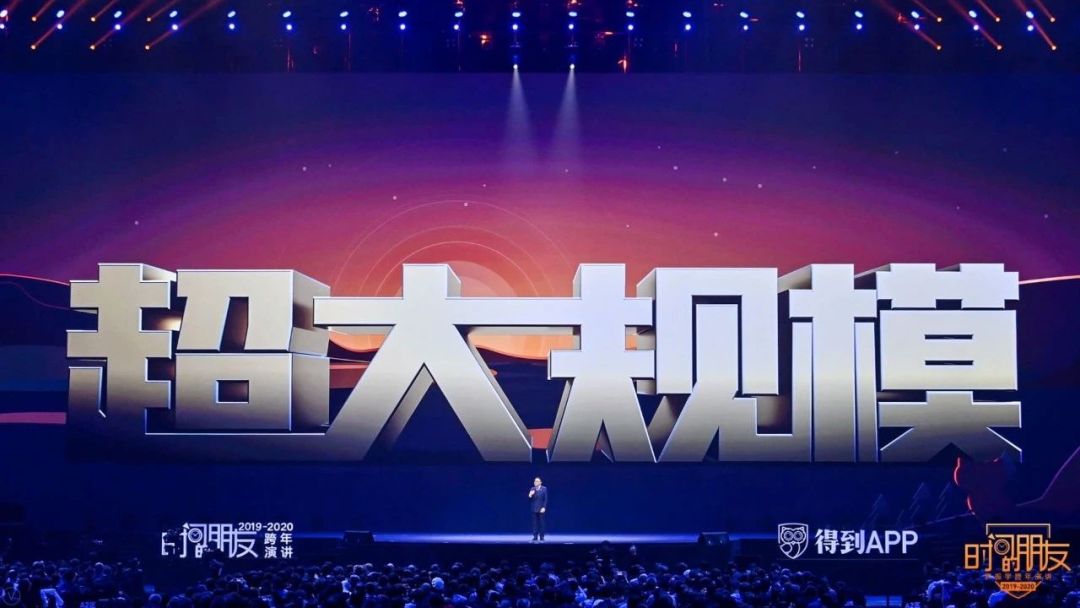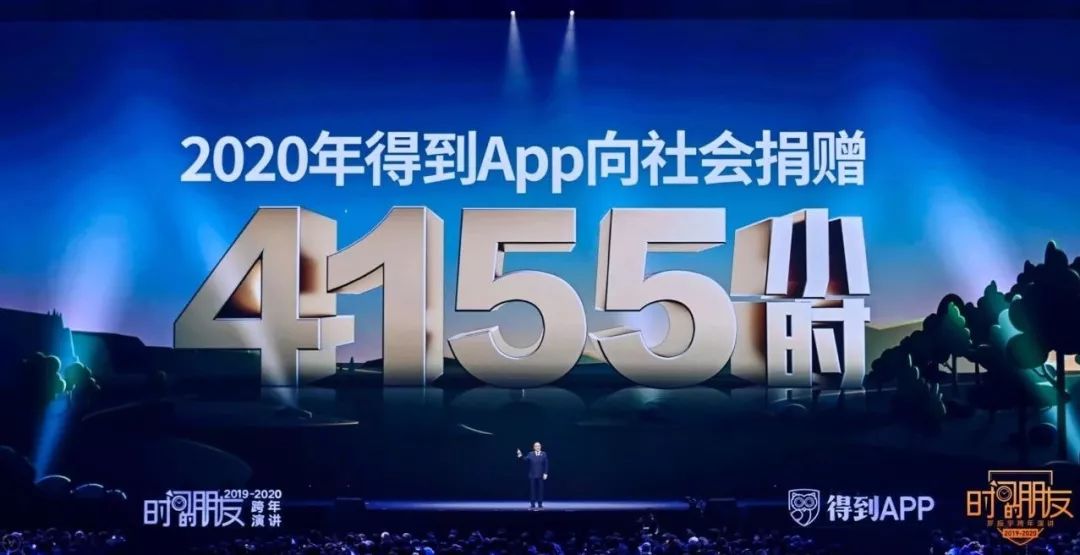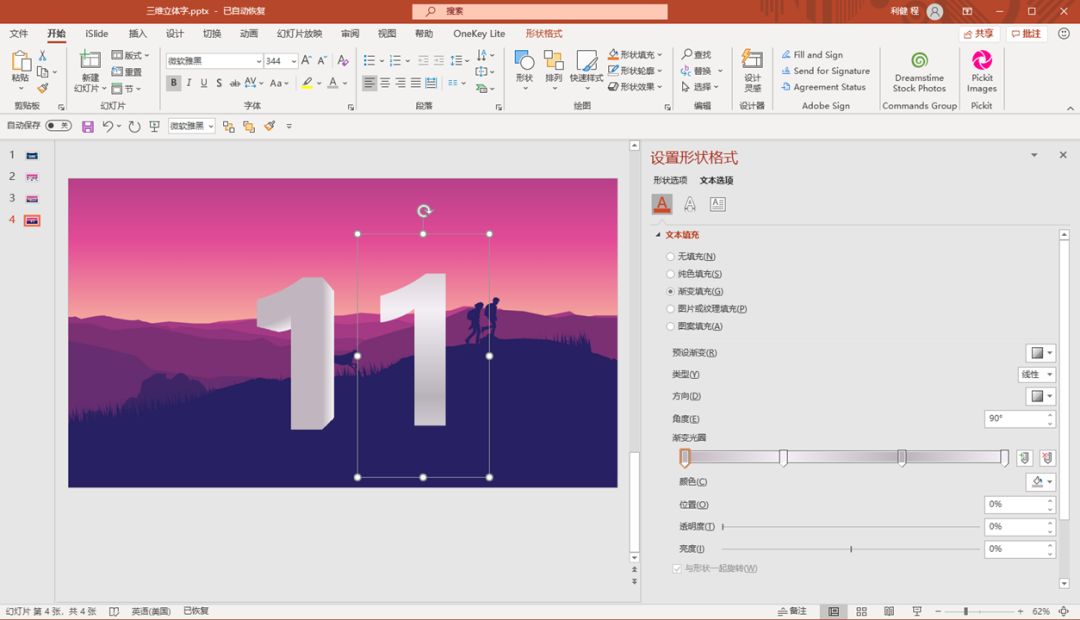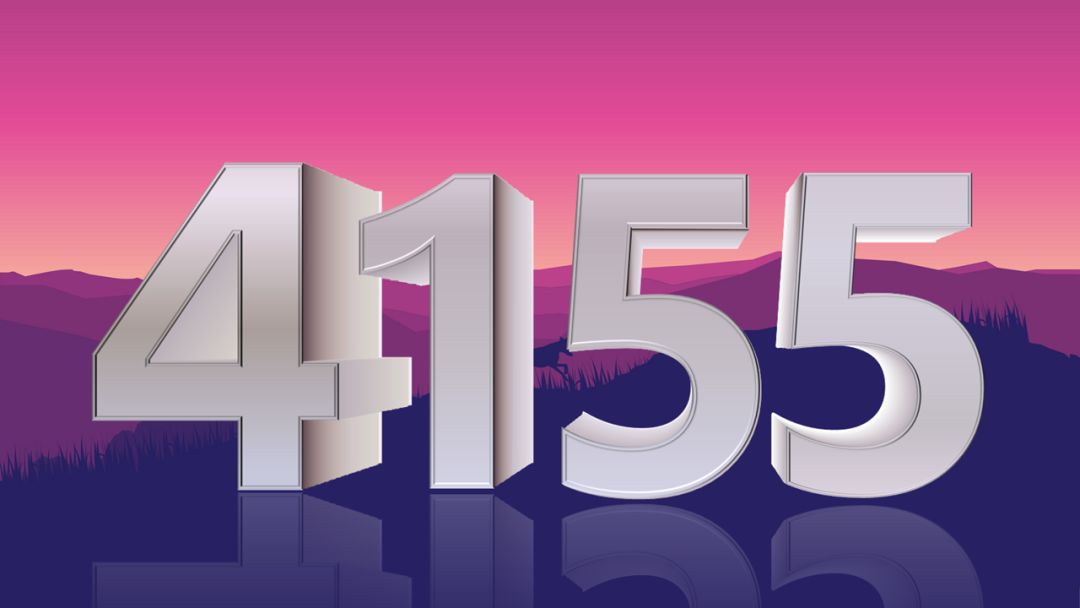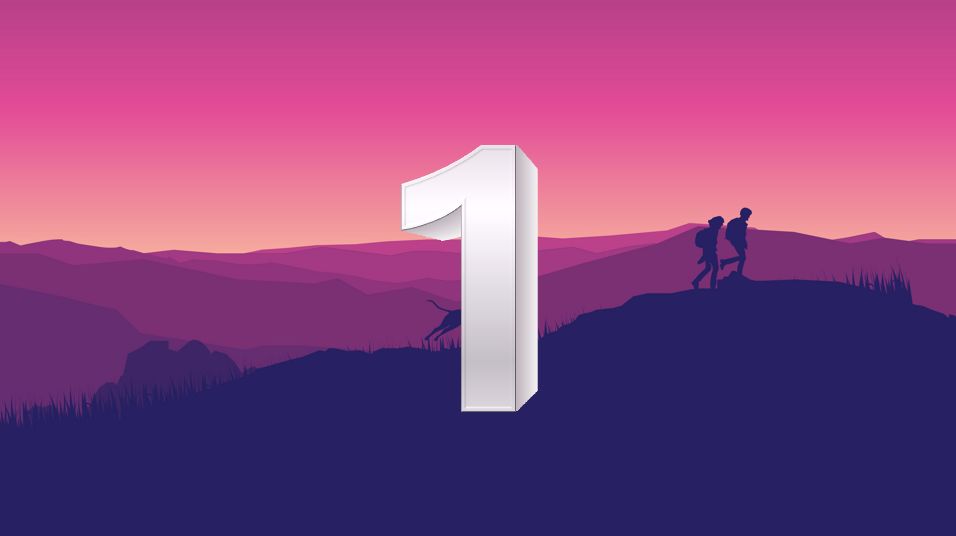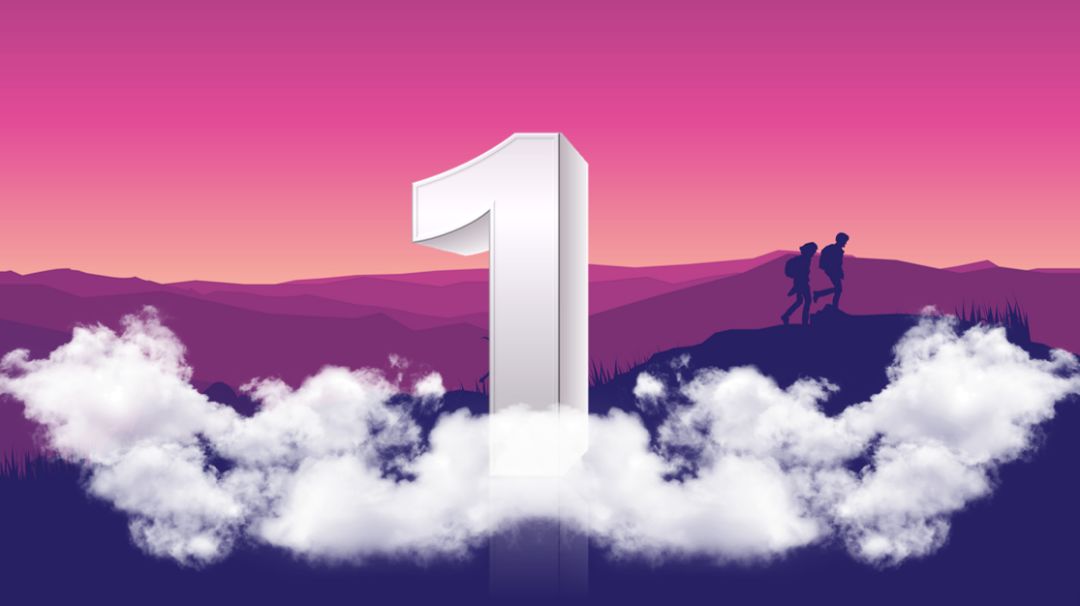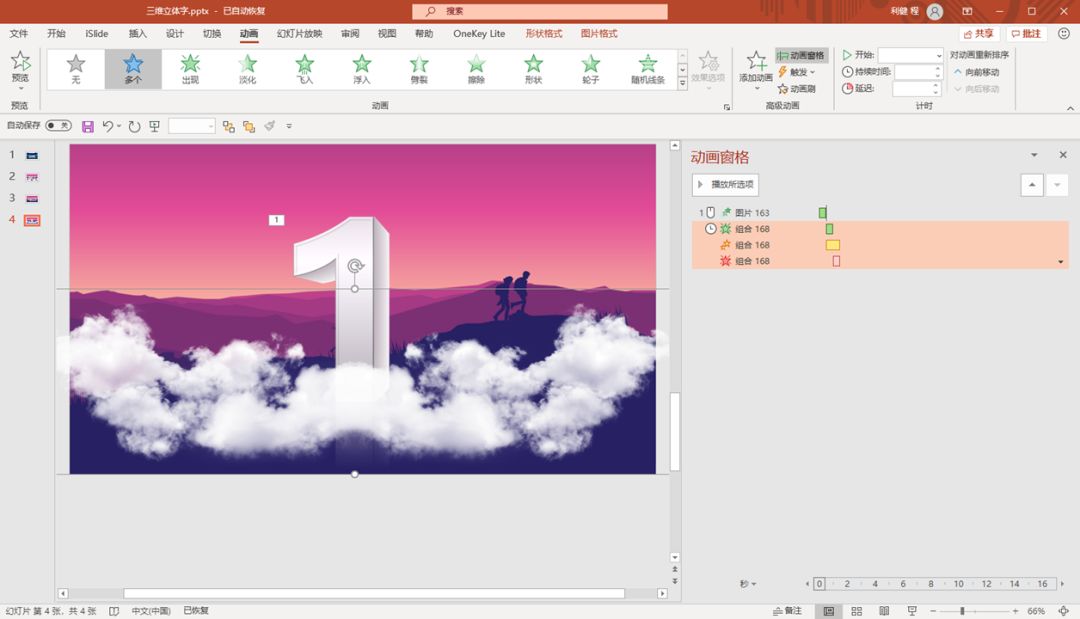
演讲PPT的立体字效果,到底是如何制作的?
很多人看了跨年演讲,问了我一个问题?像下图这样的三维立体字,用PPT到底该如何制作?
看着确实很酷,但是实话说,这个肯定不是PPT制作的。但是用PPT能不能制作类似的效果呢?
这是可以的,所以接下来,我们来制作一下三维立体字,先看一下PPT制作的成品。
这是动态的,我们来看一下静态的
三维立体字
那么这样的效果是如何制作的呢?接下来,我一步步拆解给大家看!
1、插入想要制作立体字的文本,并且复制一个,缩小一下字号,更改一下颜色,一深一浅,按照下图这样进行摆放。
2、同时选中两个文本框,我们选择islide插件下的补间动画,补间的数量大概有个七八十个就可以了。
这样我们就实现了两个文本之间的颜色的“平滑”过渡,也就是立体感的初步形成。
3、我们在原始的文本上面,设置一下文本的渐变色还要三维效果。
渐变色,我们按照下图这样去调整渐变光圈。深色交替,有一种金属质感的效果。
三维效果,我们选择,我们按照下图这样去调整三维效果。深色交替,有一种金属质感的效果。
然后,我们将得到的数字,放到补间动画后的数字上面,这样数字轮廓会更清晰。
4、我们全选数字和补间动画,复制一下,然后右键粘贴为图片。然后,我们将图片稍微裁剪一下。
5、将裁剪后的图片设置一下映像效果,调整好透明度和距离。
其它的数字,我们按照相同的方法去制作也可以实现这样的效果。
轰然落地动画
开头的这个动画,其实是keynote的动画,叫轰然落地,我们用Powerpoint也可以实现,只不过需要通过组合动画。
1、首先,我们对数字设置一个飞入动画,方向是从上向下。
2、我们插入烟雾的素材,复制一个,左右对称摆放好,然后将烟雾组合在一起。
3、这里我们对烟雾设置一个组合动画,而且是同时进行。
• 先是进入动画,我们用的淡化
• 然后是强调动画,我们用的放大
• 最后退出动画,我们用的淡化
通过这样的设置,我们就可以得到这样一个轰然落地的动画效果。
是不是还挺不错的,如果是演示现场播放,这个动画还是很震撼的。